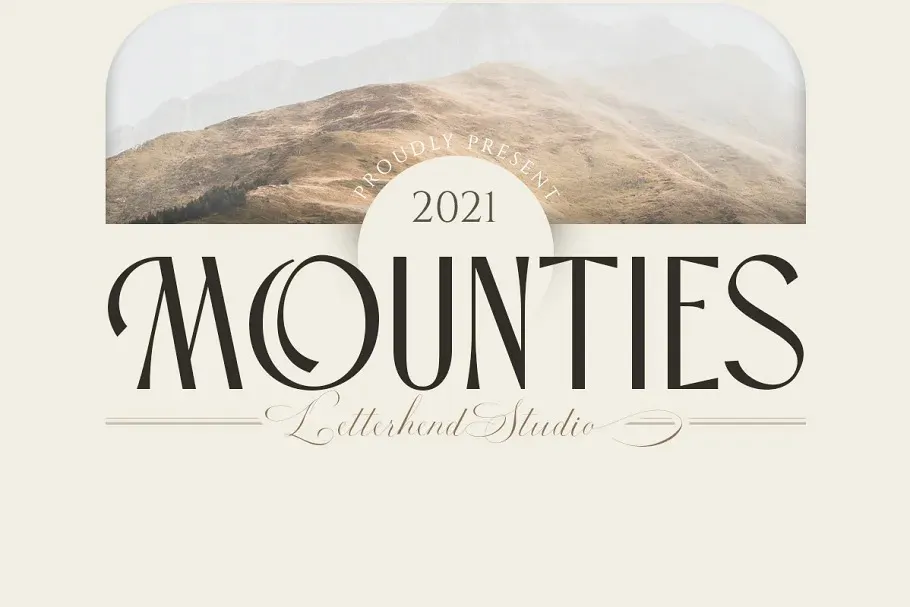
A “Mounties Font” é uma fonte sans-serif inspirada na estética geométrica, revigorada com um toque moderno que remete aos tempos retro das placas de sinalização clássicas. Esta fonte oferece alternativas e ligaturas estilizadas que a tornam única e distintiva no mercado de tipografia. Perfeita para uso em logotipos, cartões de visita, embalagens, livros de moda ou maquiagem, este design moderno é ideal para qualquer tipo de publicidade. Com seu estilo arredondado e formas geométricas, a “Mounties Font” se destacará no meio de um campo de letras sem serifas. Este é o complemento perfeito para designers que buscam uma fonte de linhas retas com uma personalidade forte e versátil para seus projetos gráficos.